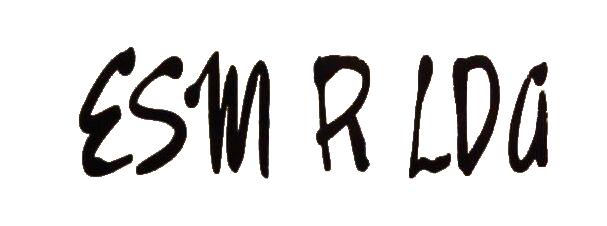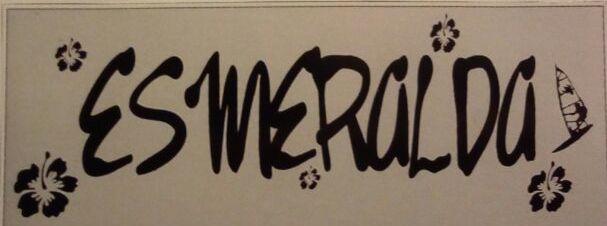
Autobeschriftung erkennen
Ich bin gerade ein bisschen am verzweifeln.
Wir hatten bisher einen VW Camping Bus der von unseren Vorbesitzern einen Namen bekommen hatte und auf der Beifahrertür augeklebt war.
Jetzt gibt es den leider nicht mehr und wir würden auf unserem Nachfolgerbus gerne eine ähnliche/gleiche Beschriftung drauf kleben.
Jetzt sind wir etwas am verzweifeln welche Schriftart das sein könnte/wie wir die Schrift ähnlich  hinbekommen.
Ich habe schon viele Schriften durchsucht aber noch nichts wirklich passendes gefunden...
Und dann beim Neubeschriften darauf achten, dass die Buchstabenabstände gleichmäßiger sind. So wie auf dem gezeigten Foto ist das ja eine einzige Katastrophe.
Bei dafont habe ich so circa 2/3 bisher durch, bisher noch nicht wirklich was  aehnliches gefunden... Weiss auch incht sicher ob s gross oder klein geschrieben ist das macht den vergleich etwas schwerer
ich habe fast ein schlechtes Gewissen, aber ich kenne jetzt leider die Antwort.
Die Schrift ist eine gestauchte „Year2000Boogie“
Gefunden war die schnell. Einfach die Grafik umgearbeitet, siehe Anlagen, und dann verfütter:
Es war bereits der Dritte Vorschlag. Jaja, Vorschläge sind auch Schläge ... *AUA*
Zu Deiner Unsicherheit wegen des A: Diese Form des Großen A kennt man aus einigen Handschriften, z.B aus den USA und aus der
Schweiz. Siehe auch den Faden über Schulschriften ... Da musst Du aber geduldig durchwühlen und einer der Anhänge auf  Seite 2 fehlt ... Miſt!